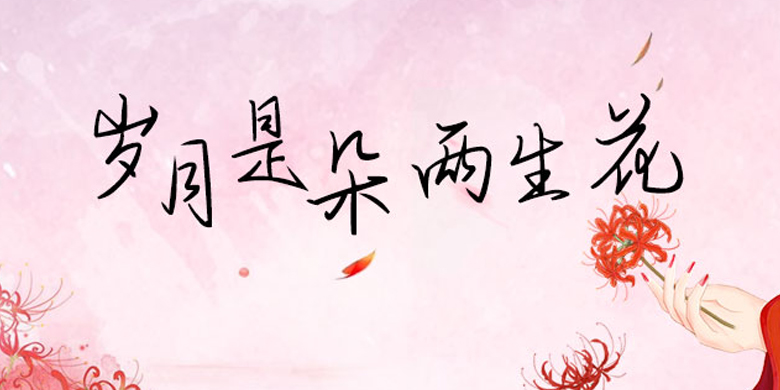
方正手迹-岁月是朵两生花
字体品牌: 方正手迹 设计师:刘晔 字体分类:常规书写·硬笔 字体属性:精品字 字符集:大陆简体(GB2312-80) 发布时间: 2020
岁月是朵两生花这款字书写流畅,连笔较多。字体整体向左倾斜,中宫收紧,笔画舒展。适用于文艺类的书刊、品牌广告和产品包装设计,以及社交网络的个性化用字。